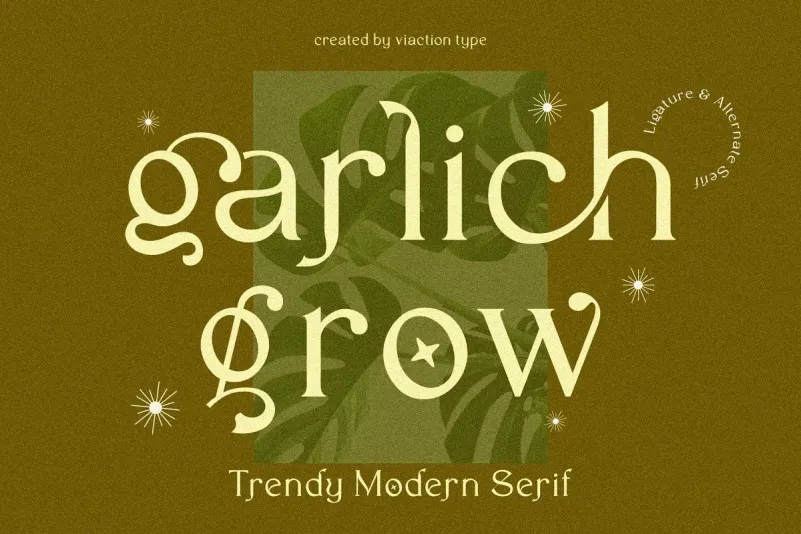
A Garlich Grow Font é uma elegante tipografia serifada ideal para projetos modernos e sofisticados. Suas linhas finas são perfeitas para quem busca personalidade e delicadeza no design de layout contemporâneo. Esta fonte abrange alternativas, ligaturas padrão e ferramentas multilíngue, tornando-a versátil e fácil de usar em diferentes projetos. Seja você um designer que precisa criar layouts modernos e elegantes ou alguém que simplesmente busca adicionar um toque sofisticado a seus trabalhos, essa fonte é uma ótima escolha. Garlich Grow oferece o equilíbrio perfeito entre simplicidade e elegância, tornando-a uma opção indispensável para quem procura uma fonte serifa moderna com ligaturas ricas.